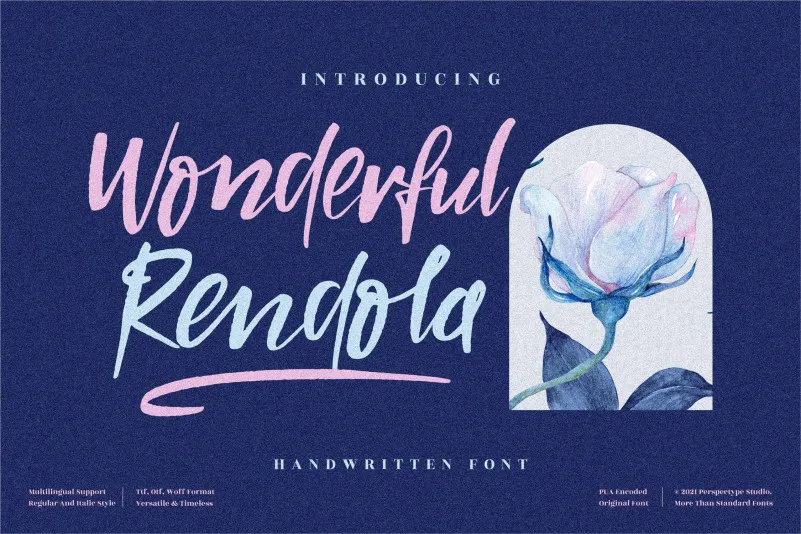
Wonderful Rendola Font – Fonte Grátis
Wonderful Rendola Font
A Wonder Rendola Font é uma elegante fórmula de escrita cursiva, com traços delicados e suaves. Ideal para criar cartões de casamento ou qualquer outro design que busque um toque romântico e personalizado. Esta fonte está repleta de características sutis que transmitem alegria e aconchego, tornando-a perfeita para momentos especiais em sua vida. Seja para aniversários, batismos ou até mesmo encontros de amigos íntimos, esta fonte oferece um toque especial e único ao seu design personalizado. Com a Wonder Rendola Font, você pode transformar simples mensagens em expressões verdadeiramente únicas, que não apenas destacam sua personalidade, mas também criam uma atmosfera mágica e encantadora para qualquer projeto de design.